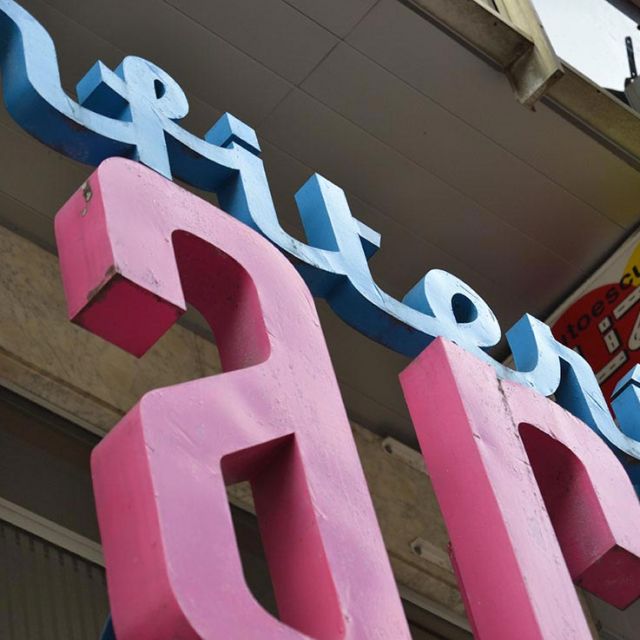
1969
[wyde_info_box title=»Tipografía» icon_set=»typicons» icon_typicons=»typcn typcn-sort-alphabetically»]Script / Sans[/wyde_info_box][wyde_info_box title=»Técnica» icon_set=»typicons» icon_typicons=»typcn typcn-brush»]Metal[/wyde_info_box]
Esta confitería santanderina, tiene su origen  en 1949 cuando junto al Pasaje de Peña en la calle Atilano Rodríguez, se abre una pequeña Heladería llamada «La Polar», heladería vinculada a la misma familia Salas que se remonta a 1888, y que después pasaría a un local vecino, donde actualmente aún se puede comprar la fruta, separándose definitivamente las dos lineas de negocio.
En 1951 abre su obrador en la Calle Justicia, y es en 1969 cuando se abre la confitería de la calle Burgos 11, con el rótulo actual que está montado y aún se puede ver. Una combinación de tipografías script y sans, con un estilo moderno para la época.
Actualmente funcionan las 2 confiterías y han sido reconocidas en 2011 por su trayectoria profesional.
Actualización: el 31 de enero de 2020 cierra definitivamente sus puertas, por la jubilación de Luis Salas Pérez.